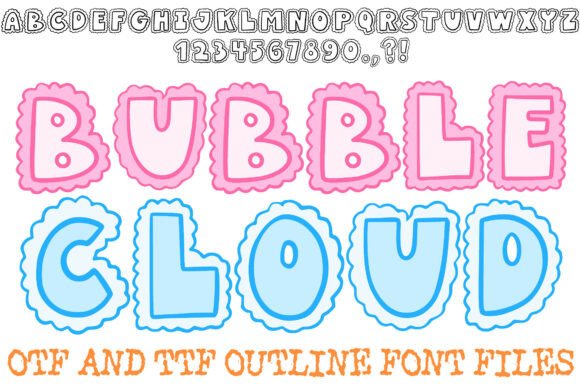
Bubble Cloud
การค้นหาองค์ประกอบการออกแบบที่เหมาะสมอาจเป็นเรื่องท้าทาย แต่ Bubble Cloud นำเสนอคอลเลกชันที่โดดเด่นซึ่งช่วยยกระดับงานของคุณได้ทันที
ไม่ว่าคุณจะสร้างผลิตภัณฑ์ POD (Print on Demand) คำเชิญงานแต่งงาน หรือกราฟิกโซเชียลมีเดีย Bubble Cloud ก็เหมาะสมอย่างยิ่ง